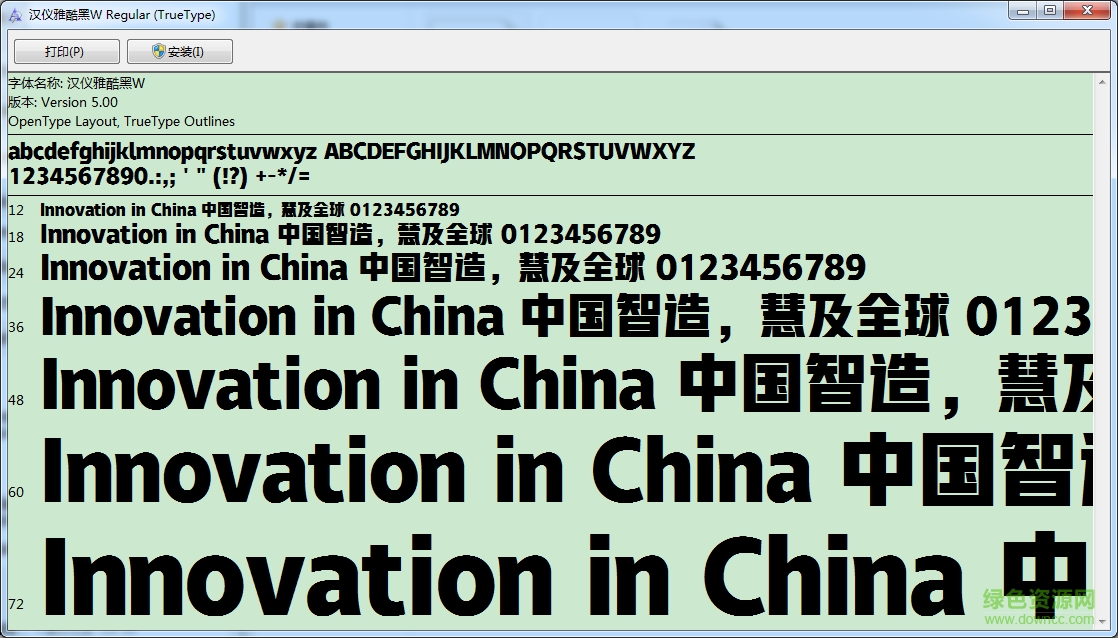
hyyakuheiw(漢儀雅酷黑)字體是一款酷酷的漢儀字體,該字體筆畫堅(jiān)毅,個(gè)性獨(dú)特,宜作雜志、文章、ppt的排版標(biāo)題,以及廣告設(shè)計(jì)用字,歡迎下載!
該字體線條非常粗壯,字形端正大方,整體效果非常出色,且字庫完整,可以廣泛應(yīng)用于橫幅標(biāo)語、美術(shù)設(shè)計(jì)、宣傳海報(bào)、ppt、影視制作以及內(nèi)容用字等領(lǐng)域,